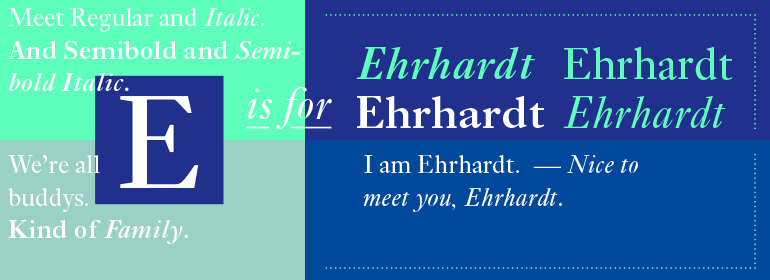
Ehrhardt®
Ehrhardt的名字表明该字体源自于荷兰字符的罗马体和斜体,该字体由莱比锡的Ehrhardt铸造厂在17世纪后期的标本中使用果。设计师的身份并不为人所知,尽管一些历史学家认为这是匈牙利设计师Nicholas Kis的作品。Monotype在1937年至1938年间为当代出版商复刻了该字体。Ehrhardt简洁整齐而且收笔处圆滑,这些特点都增强了该字体的可读性,而且略显细窄,尤其斜体更为明显,这样能够节省空间。Ehrhardt是一款精美的文本字体,尤其是对于书籍。
The Ehrhardt name indicates that this typeface is derived from the roman and italic typefaces of stout Dutch character that the Ehrhardt foundry in Leipzig showed in a late-seventeenth-century specimen book. The designer is unknown, although some historians believe it was the Hungarian Nicholas Kis. Monotype recut the typeface for modern publishers in 1937 to 1938. Ehrhardt has a clean regularity and smooth finish that promote readability, as well as a slight degree of condensation, especially in the italic, that conserves space. Ehrhardt is a fine text face, especially for books.